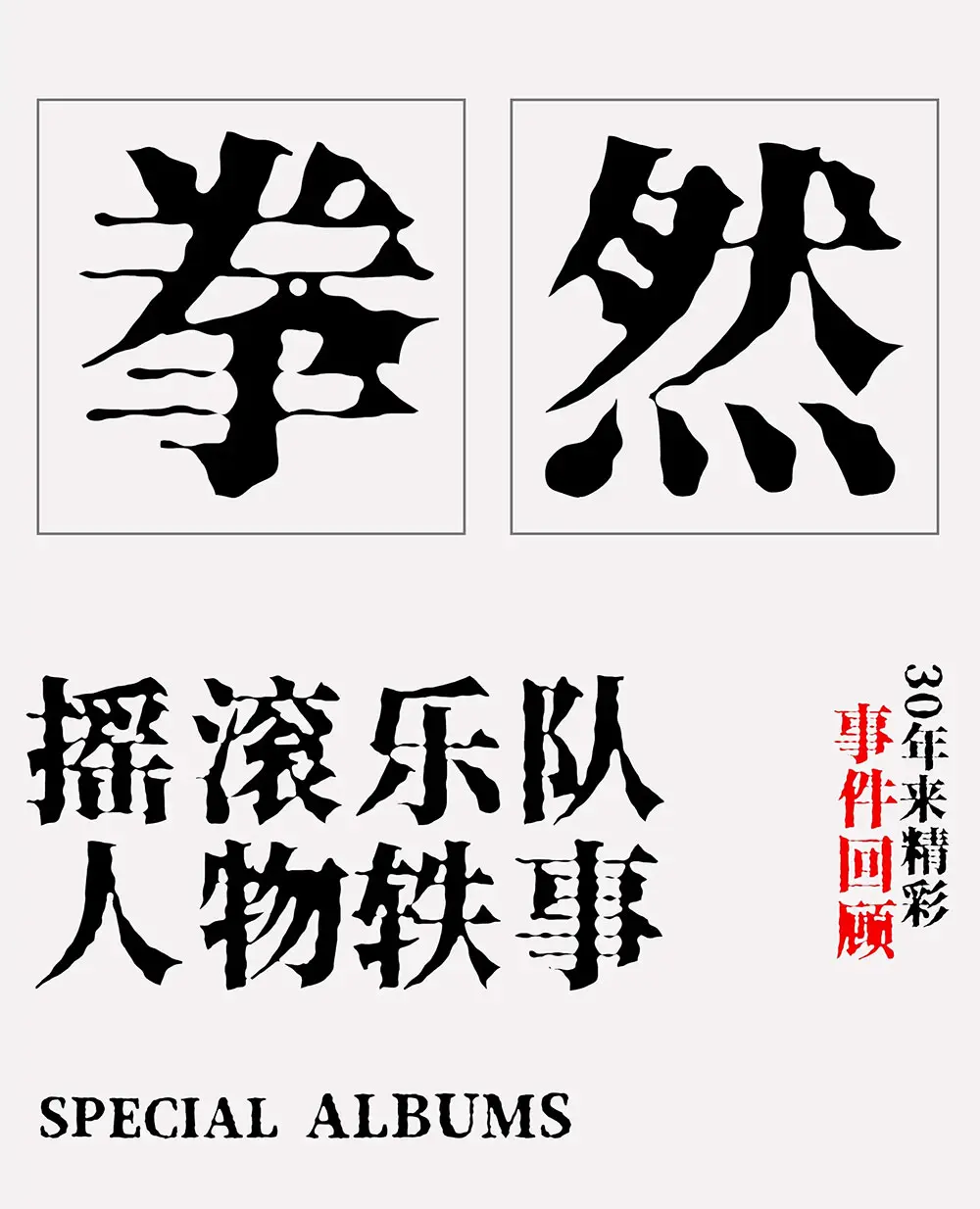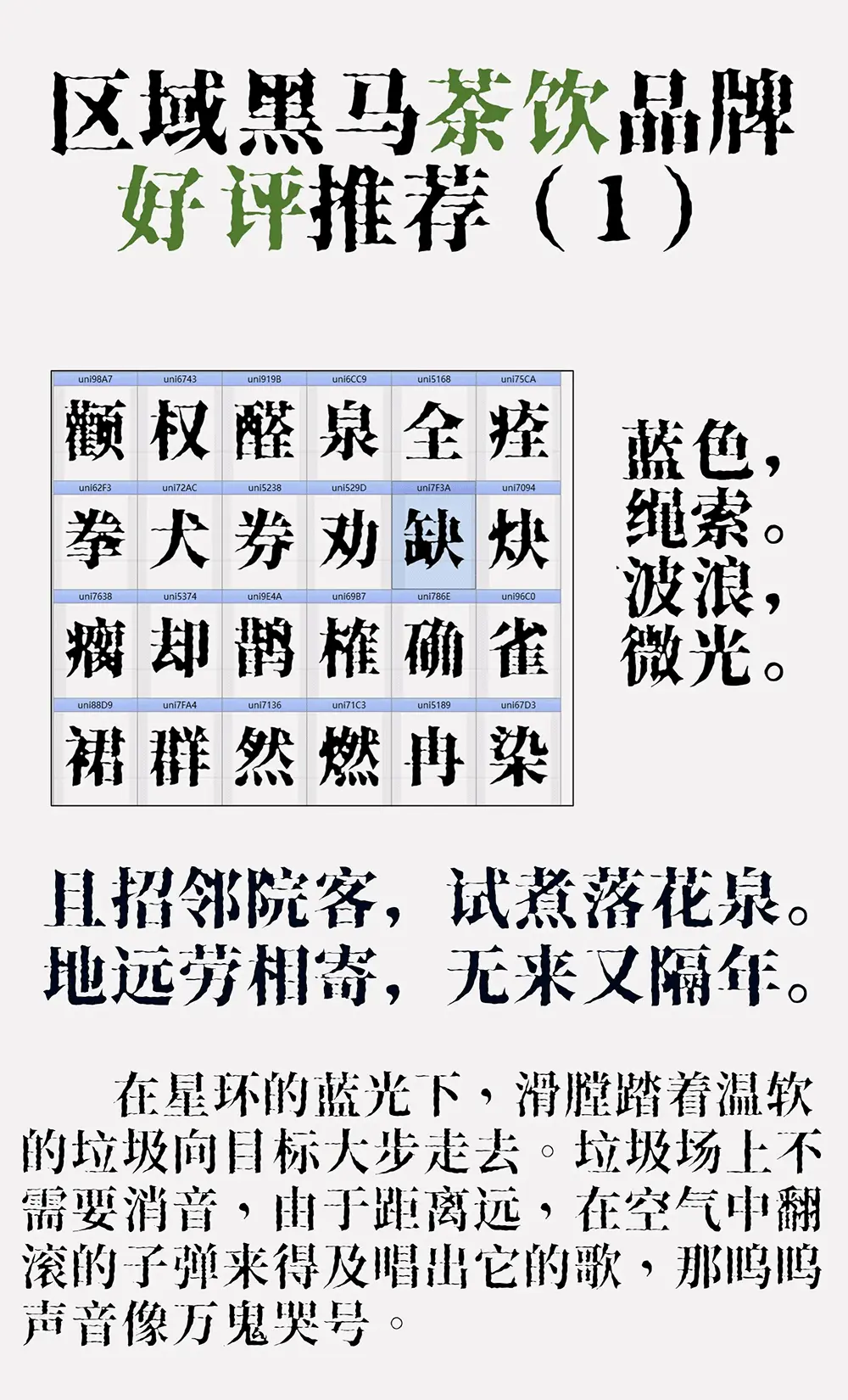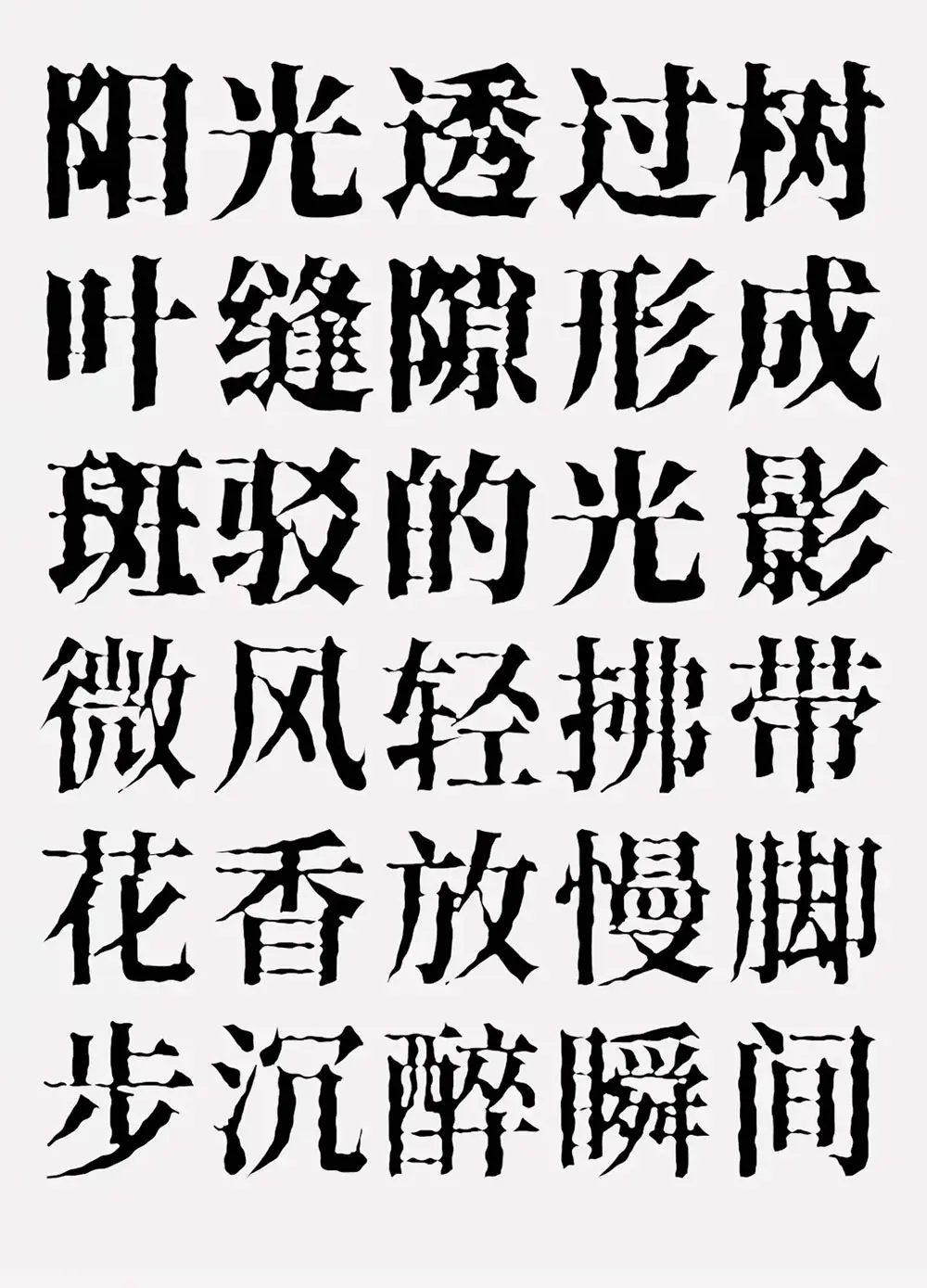
香萃打字機體預覽
香萃打字機體介紹
香萃打字機體系列是一款筆畫模仿打字機洇墨效果的宋體字家族,包含3個字重。字體的原型是開源項目思源宋體。其中W40與W35的區別在於漢字橫畫粗細、細節的粘連程度,以及英文字母襯線的不同。製作過程經歷人工手動調節,因此目前僅支持GB2312的約7000字符。製作這款字體,是由於先前的香萃刻宋的線條過於尖銳,在偏大字號時顯示效果不好。